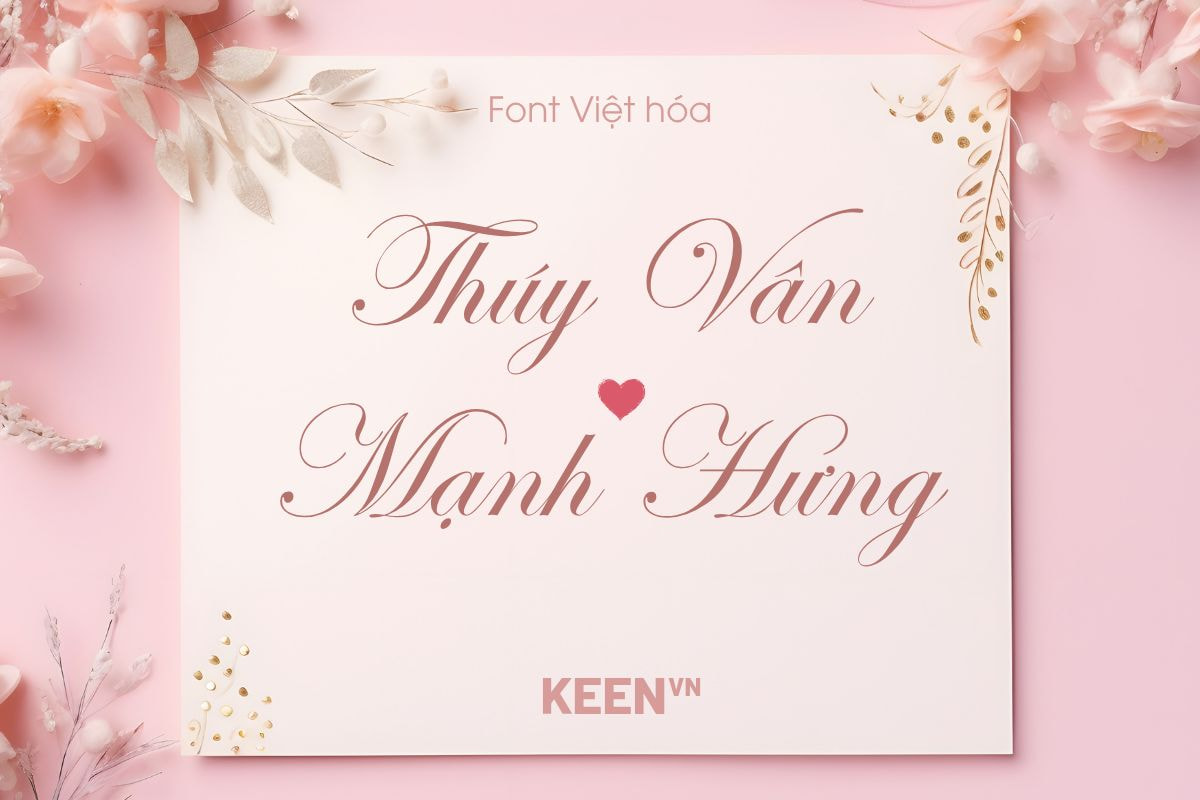
Font Việt hóa SFU Edwardian Script Regular
- Hỗ trợ đầy đủ dấu tiếng Việt
Font Edwardian Script việt hóa là một phông chữ thanh lịch và tinh tế, lấy cảm hứng từ phong cách chữ viết tay thời kỳ Edwardian. Thời kỳ Edwardian, kéo dài từ cuối thế kỷ 19 đến đầu thế kỷ 20, được biết đến với vẻ đẹp tinh tế và sang trọng trong nghệ thuật và thiết kê.
Đặc trưng của Font Edwardian Script việt hóa là những đường nét mảnh mai, uyển chuyển, phản ánh sự sang trọng và quý phái. Font này thường được sử dụng trong các thiết kế cần sự thanh lịch, như thiệp mời, logo, tiêu đề, và cả trong thiết kế sách. Nó phù hợp với các dự án mà bạn muốn truyền tải một cảm giác cổ điển, lịch sự và cao cấp.
Font Edwardian Script việt hóa cũng thường được chọn lựa trong việc thiết kế các ấn phẩm cưới hoặc sự kiện đặc biệt khác, nơi mà sự tinh tế và duyên dáng được đề cao. Phông chữ này không chỉ mang lại vẻ đẹp visu mà còn giúp tạo nên một ấn tượng sâu sắc và lâu dài trong tâm trí người xem.